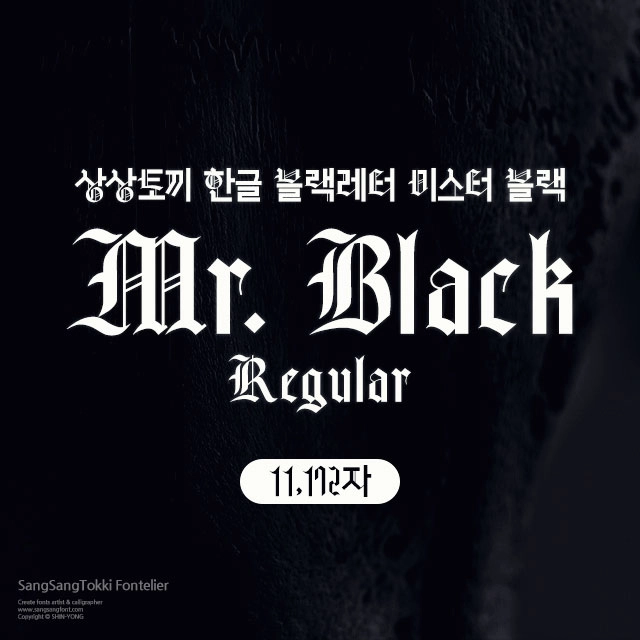
미스터블랙 2종
상상토끼의 한글 블랙레터 폰트 첫번째 시리즈, 미스터 블랙 2종
한글 11,172자 / 영문 52자 / 약물 84자
미스터블랙 Regular 1종
미스터블랙 Oblique 1종
| 블랙레터라 함은 획이 두껍고 글자의 폭이 좁아서 이름 그대로 지면이 검게 보이는 글자체를 의미합니다. 서양 문화 최초의 금속활자 인쇄본으로 알려진 구텐베르크 성경에 활자로 사용된 서체입니다. |
| 획이 가로에서 세로로 바뀔때 부드럽게 곡선으로 굴려지지 않고 딱딱하게 꺾어서 쓰기 때문에 '꺾어 쓰는 글자체'라고 부르기도 합니다. |
| 블랙레터의 형태는 시간과 장소가 바뀌면서 변화하게 됩니다. 꺾어 쓰는 글자로 딱딱한 이미지를 가졌던 텍스투라는 이탈리아로 건너가서 폭이 넓고 둥근 로툰다로 변화했습니다. 그후 독일에서는 르네상스 시대에 슈바바허, 바로크 시대에 프락투어로 진화해 20세기로 이어졌습니다. |
| 블래레터는 20세기 중반까지도 독일에서 널리 쓰였는데요, 그중 프락투어는 2차대전 당시 히틀러가 나찌 프로파간다에 주로 사용했던 글자체이기도 합니다. 그때문에 당시에는 블래레터에 부정적인 인식이 생기기도 했습니다. |
| 블랙레터의 여러 형태 중에서 심플하고 굵은 획과 절도있는 꺾임을 핵심 요소로 가지고 있는 텍스투라를 상상토끼의 첫번째 한글 블랙레터로 선보입니다. 가독성을 심각하게 해치지 않을만큼의 꾸밈 요소만 사용한 심플한 서체로 마무리 할 예정입니다. |